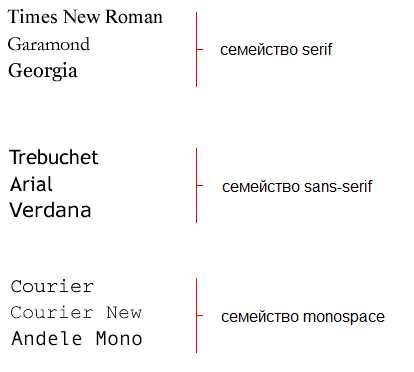
Работа со шрифтами в CSS – это не просто выбор красивого начертания. От корректного подбора и подключения шрифта зависит читаемость текста, визуальный баланс страницы и общее восприятие контента пользователем. Используя свойства CSS, можно управлять гарнитурой, размером, насыщенностью, межстрочным интервалом и другими характеристиками шрифта без сторонних инструментов.
Для начала стоит определить, какие шрифты будут использоваться. Свойство font-family задаёт основной и резервные варианты, что обеспечивает корректное отображение текста даже при отсутствии нужного шрифта на устройстве пользователя. Например: font-family: «Open Sans», Arial, sans-serif; – здесь браузер последовательно проверит наличие шрифтов, подставив ближайший доступный аналог.
Чтобы применить собственный шрифт, используется директива @font-face. Она позволяет подключить локальные файлы шрифта форматов WOFF2, WOFF или TTF. Рекомендуется хранить их в отдельной папке, например /fonts/, и указывать несколько форматов для кроссбраузерной поддержки. Такой подход делает сайт независимым от системных шрифтов и гарантирует единый стиль отображения на всех устройствах.
После подключения можно детально настроить внешний вид текста с помощью свойств font-size, font-weight, line-height и letter-spacing. Грамотное использование этих параметров помогает добиться чёткого визуального ритма и адаптивности типографики под разные экраны. Всё это делает CSS основным инструментом для точного управления шрифтами без потери производительности и визуального качества.
Подключение системных шрифтов через свойство font-family
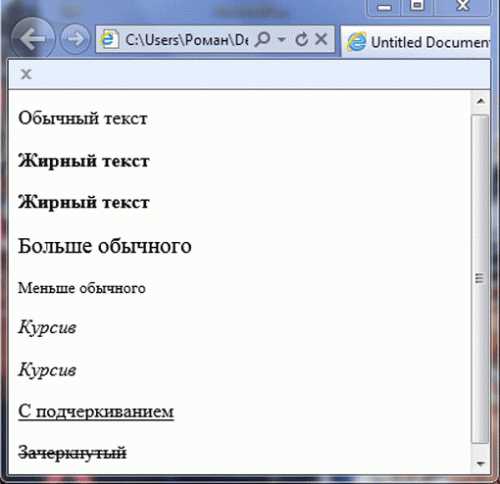
Свойство font-family позволяет указать несколько шрифтов подряд, формируя стек: если первый недоступен, браузер применит следующий. Завершать список следует универсальным семейством – serif, sans-serif, monospace, cursive или fantasy.
В этом примере задействованы популярные системные шрифты:
-apple-system– интерфейсный шрифт macOS и iOS;BlinkMacSystemFont– аналог для браузеров на движке Blink;"Segoe UI"– стандартный шрифт Windows;Roboto– базовый шрифт Android;OxygenиUbuntu– типичные варианты для Linux;"Helvetica Neue"– запасной шрифт для старых macOS;sans-serif– универсальное семейство на случай отсутствия всех предыдущих.
Рекомендуется тестировать отображение на разных платформах, так как названия системных шрифтов могут отличаться. Для корпоративных проектов полезно определить собственный набор приоритетных шрифтов с учетом целевых устройств и интерфейсных стандартов.
Использование веб-шрифтов с помощью @font-face
@font-face позволяет подключать нестандартные шрифты напрямую, без зависимости от системных библиотек пользователя. Правильное подключение гарантирует стабильное отображение текста на любых устройствах.
Базовый синтаксис включает указание имени шрифта и путей к его файлам разных форматов. Форматы нужны для совместимости с различными браузерами:
Свойство font-display: swap ускоряет отображение текста, заменяя его системным шрифтом до загрузки основного. Для оптимальной работы рекомендуется использовать WOFF2 – он обеспечивает лучшее сжатие и скорость загрузки.
После объявления шрифта его можно применить к любым элементам:
| WOFF | Все основные браузеры | Хорошая совместимость, умеренное сжатие |
| TTF/OTF | Большинство систем и браузеров | Гибкость, но больший размер файлов |
| SVG | Старые версии iOS | Редко используется, устаревший формат |
Для ускорения загрузки используйте локальные копии шрифтов и минимизируйте количество подключаемых начертаний. Проверяйте корректность лицензии перед размещением шрифта на сервере.
Настройка запасных шрифтов и каскадирование семейства
Чтобы текст корректно отображался на любых устройствах, важно указать цепочку запасных шрифтов через запятую в свойстве font-family. Если основной шрифт недоступен, браузер последовательно применит следующий. Пример: font-family: «Roboto», «Segoe UI», Arial, sans-serif;.
Последний элемент в списке должен быть общим семейством – serif, sans-serif, monospace, cursive или fantasy. Это гарантирует читаемость даже при отсутствии всех предыдущих шрифтов.
Рекомендуется подбирать запасные варианты с похожими пропорциями и межбуквенным интервалом, чтобы избежать визуальных сдвигов. Например, для «Open Sans» подойдут «Helvetica Neue» и Arial.
Как изменить толщину и наклон текста с помощью CSS?
Толщина текста меняется свойством font-weight, которое принимает значения от 100 до 900 или ключевые слова, например, normal и bold. Для наклона текста используется font-style с параметрами normal, italic или oblique. Эти свойства можно комбинировать, например: font-weight: 700; font-style: italic;, чтобы текст был жирным и наклонным одновременно.